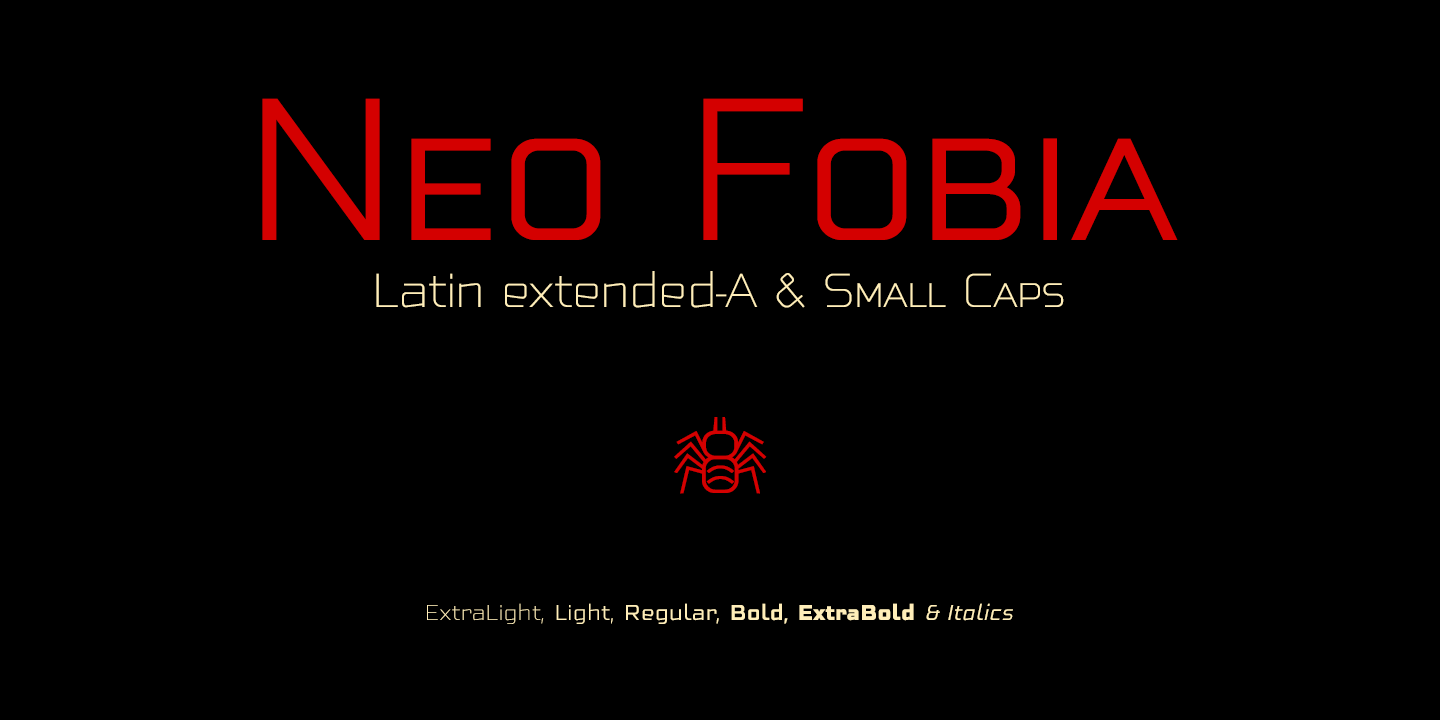
Neo Fobia Typefaces
A Neo Fobia é uma família de tipo sans serif que traz letras em maiúsculas menores, apresentando 10 fontes exclusivas com proporção quadrada e estilo tecnológico, desenhadas para uma máxima legibilidade com um aspecto minimalista. Lançada em 2019, esta família abrange uma linguagem visual robusta e moderna que se destaca por sua simplicidade e eficiência visual. Com suas linhas puras e formas geométricas, a Neo Fobia não apenas oferece uma leitura fluida e precisa, mas também uma correta representação de características como títulos e nomes. O designer defharo criou este tipoface com um olhar atento para a legibilidade e ao tempo moderno, resultando em uma fonte que se ajustará perfeitamente tanto para uso em ambientes digitais quanto impressos. Esta família de tipos não apenas oferece uma ampla gama de opções para designers gráficos, publicitários e webmasters, mas também proporciona um design sofisticado e moderno com características elegantes. A Neo Fobia é perfeita para qualquer projeto que exija uma fonte forte e poderosa, tanto em aplicativos digitais quanto impressos, garantindo leitura clara e aprimorando o impacto visual de seu trabalho.